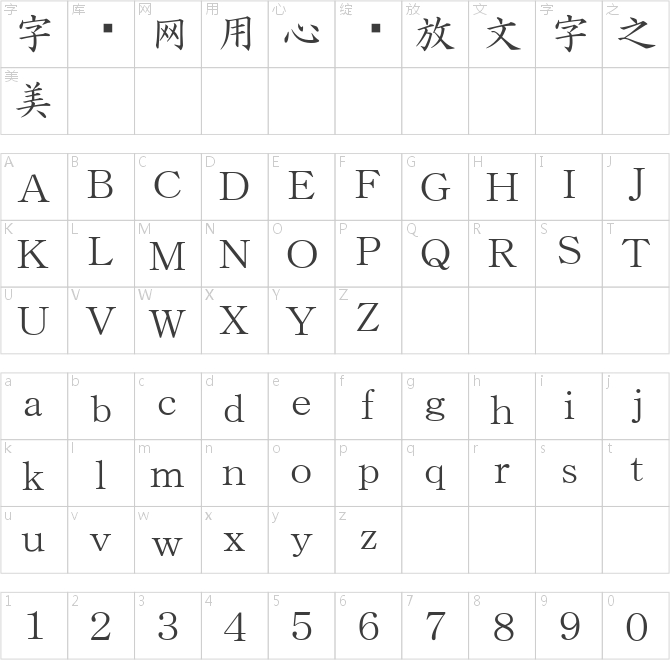
字体名称: 真宗聖典楷書
真宗聖典楷書
真宗聖典楷書介绍
真宗圣典楷书是日本“净土真宗圣典”系列字体的其中一款。这个字体是为了将日本佛教「净土真宗派」的各大经典电子化而开发的字体,字体字形还原原书,颇具旧时楷书风韵。
真宗聖典楷書字体ShinshuSeitenKaisho真宗圣典楷书字库是一款让人赏心悦目、百看不厌的中文字体,适合各类广告和产品包装设计应用,字体大小4.46MB,格式为ttf字体,上传用户是芊荨文化①,作者/版权方为ARIKUNI Tomomitsu